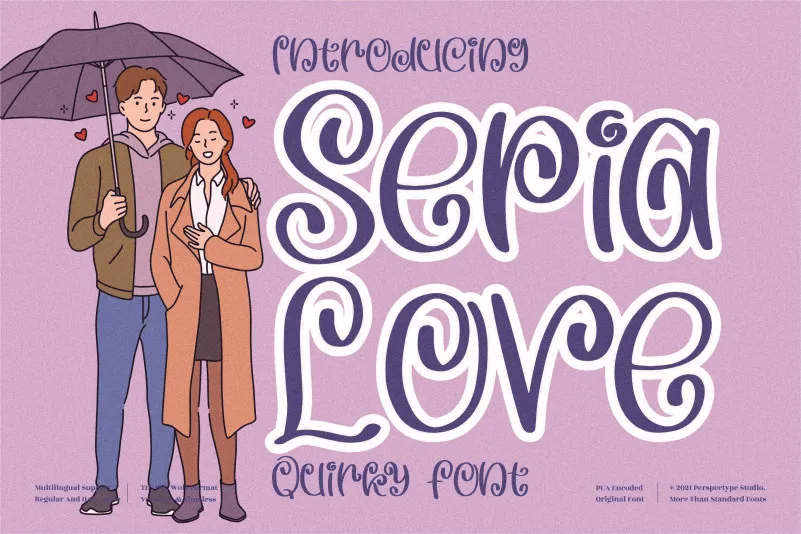
A Sepia Love Font é uma elegante fonte cíliar com um toque divertido e moderno, perfeita para quem busca uma mistura única de sofisticação e personalidade vibrante no seu trabalho visual. Esta opção Playful Fonts da designer perspectype oferece uma textura suave e delicada que pode ser usada em variados contextos, do design editorial até o branding pessoal. Se você quer agregar um toque especial a suas criações, esta fonte cíliar é perfeita para torná-las ainda mais únicas e memoráveis. Não se surpreenda com os resultados que ela pode produzir; com Sepia Love Font, seu design ficará ainda melhor.